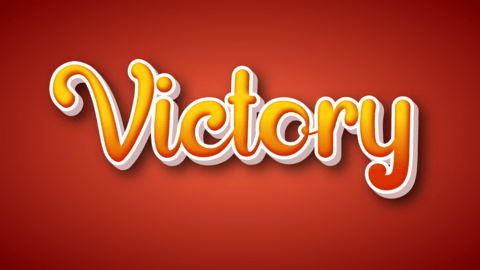
Glanzende karamel cheesecake 3D bakkerij typografie-effect
Maak watertandende beelden met dit weelderige, glanzende 3D-teksteffect dat de rijke, romige essentie van met karamel bedruppelde cheesecake vastlegt, perfect voor zoete, uitnodigende ontwerpen en bakkerijthema-projecten.